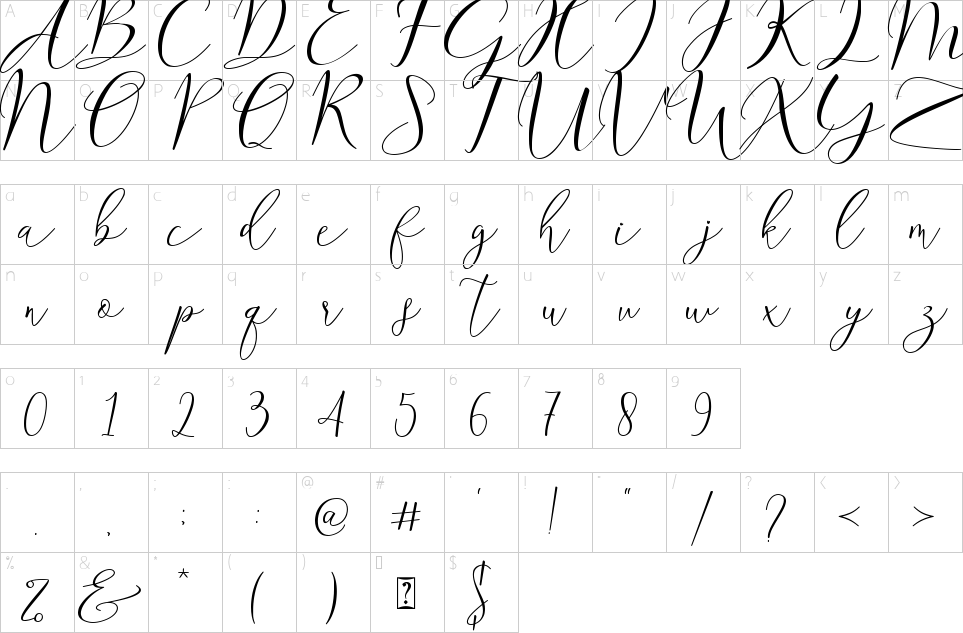
A Gading é uma fonte linda e elegante que se encaixa perfeitamente para vários estilos de design. Desenvolvida pela Nox Studio, essa fonte foi criada para ajudar designers a adicionar um toque único ao seu trabalho. Com seus traços delicados e curvas suaves, a Gading é uma escolha ótima para criações que valorizam esse tipo de sofisticação e elegância minimalista. Como uma fonte gratuita, ela se destaca como uma opção versátil e prática para aqueles que buscam adicionar personalidade sem comprometer os recursos do seu projeto. Com downloads já superando o milhar, a Gading tem ganhado popularidade por sua facilidade de uso e beleza visual. Se você está procurando pela perfeita fonte para dar um toque único ao seu design digital, vale a pena considerar a Gading.